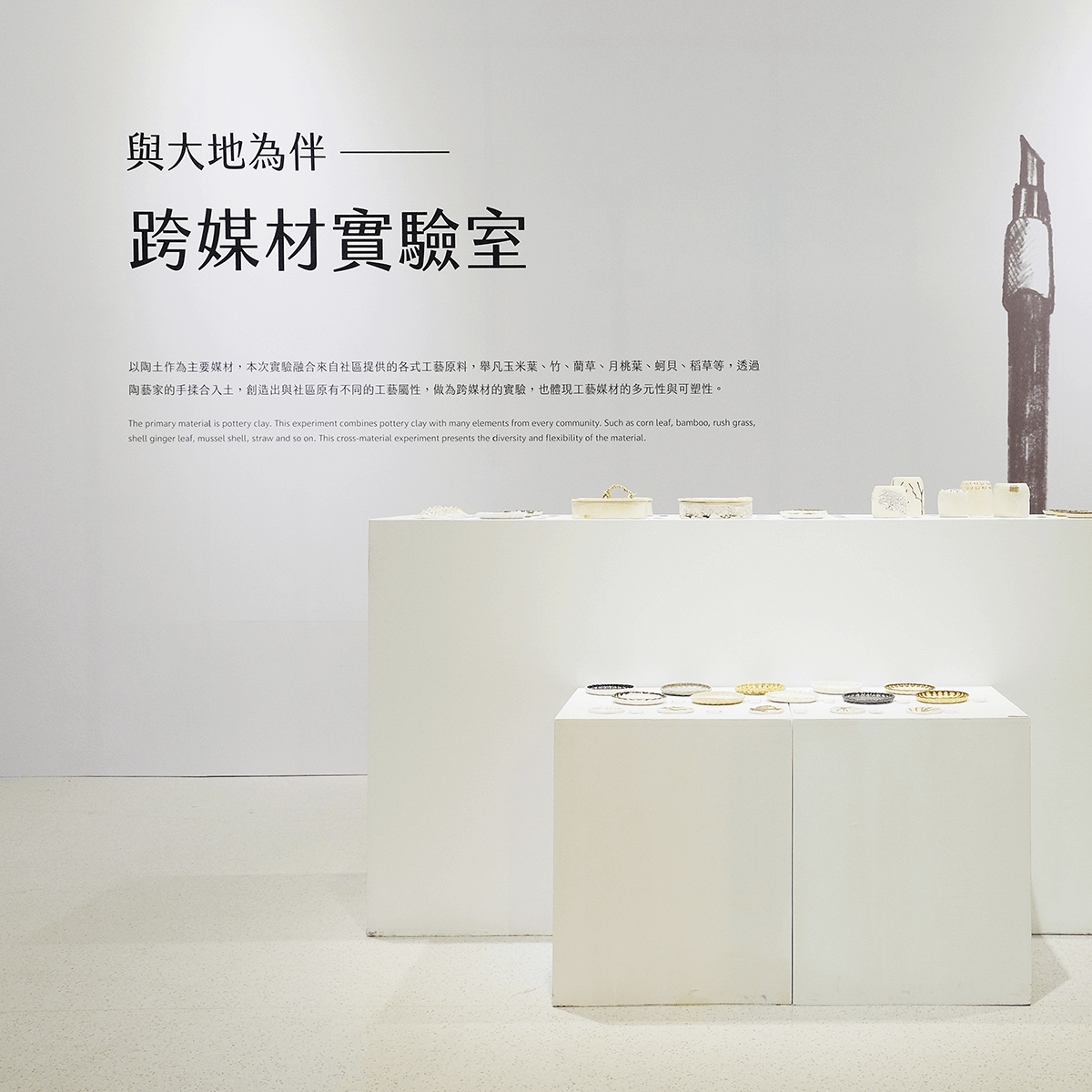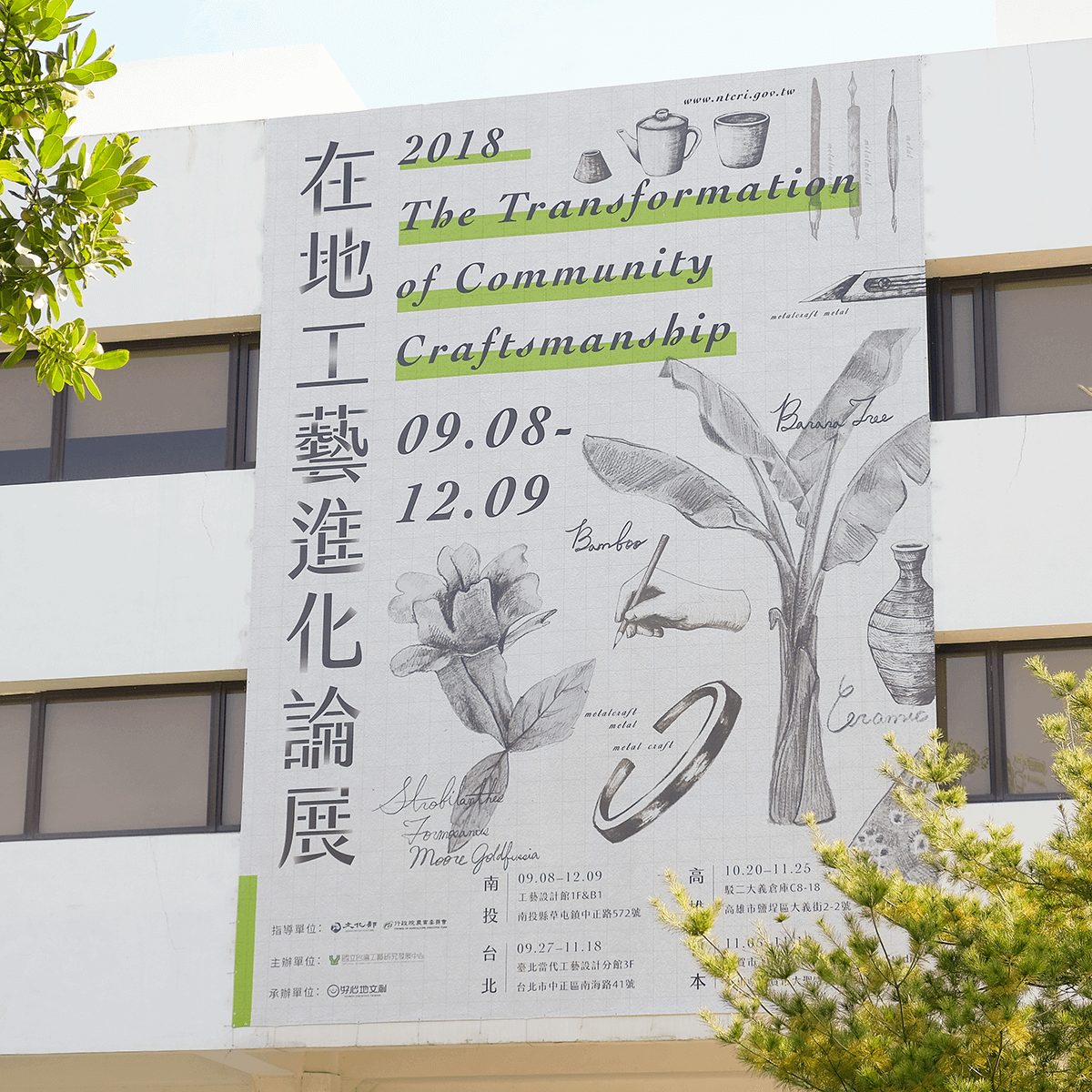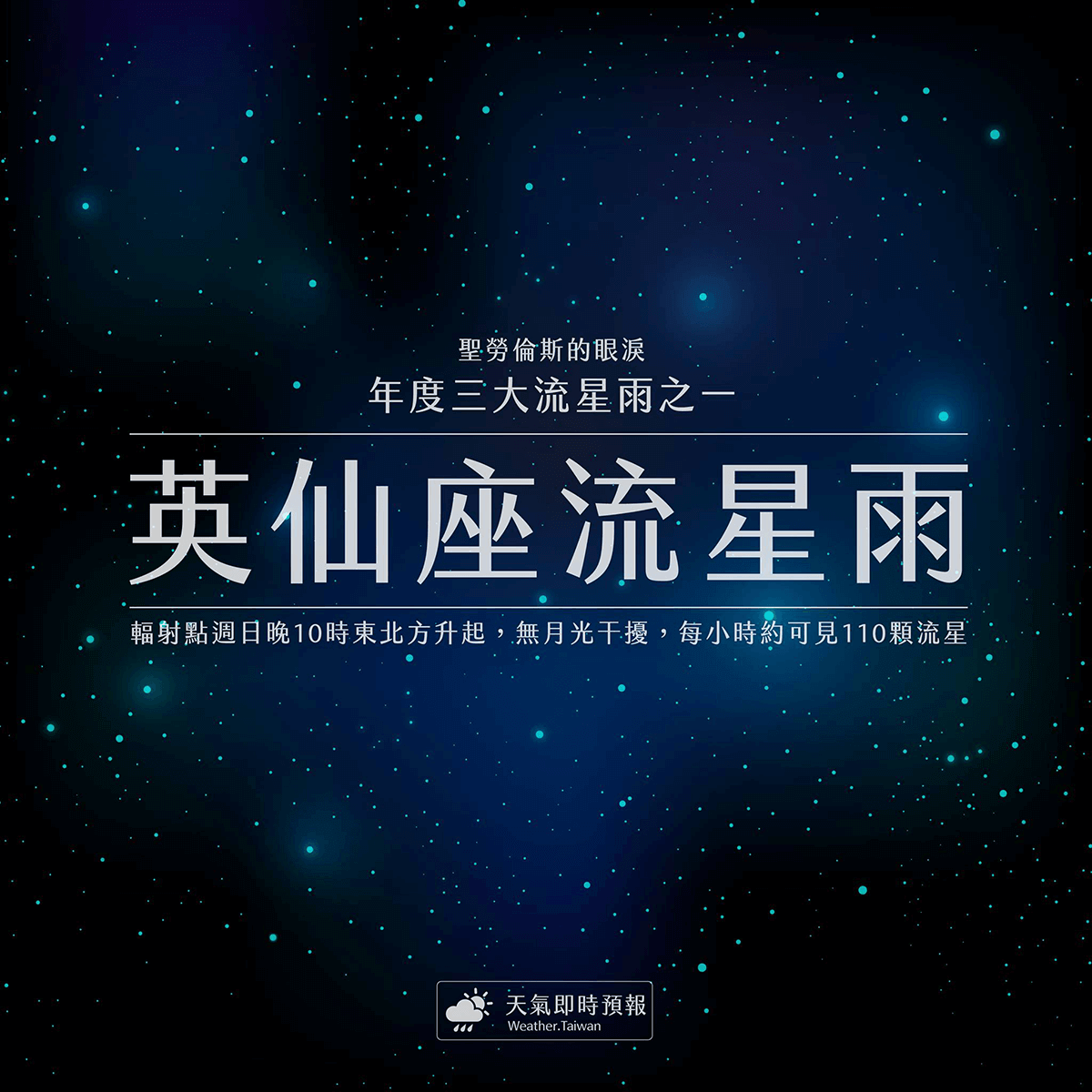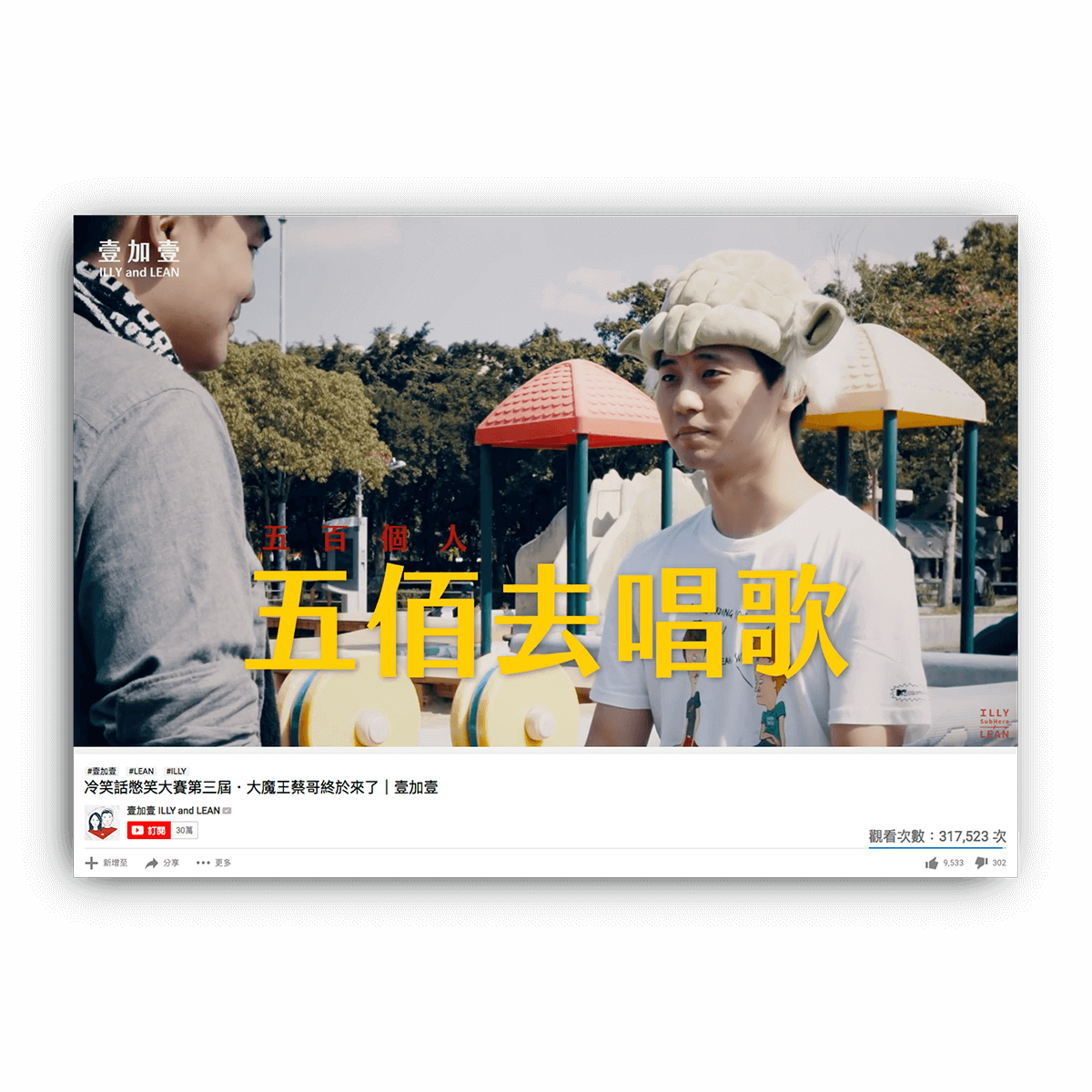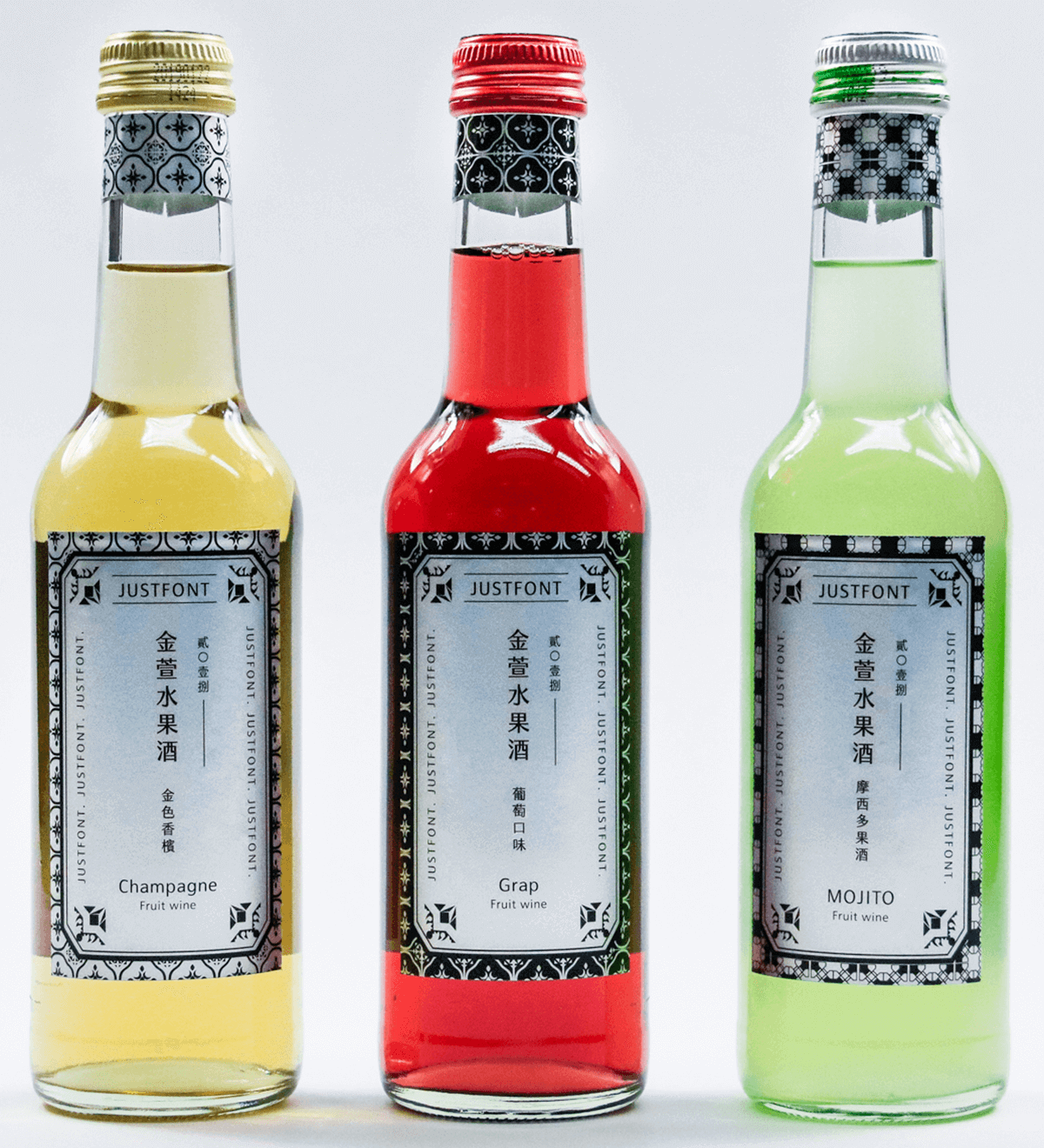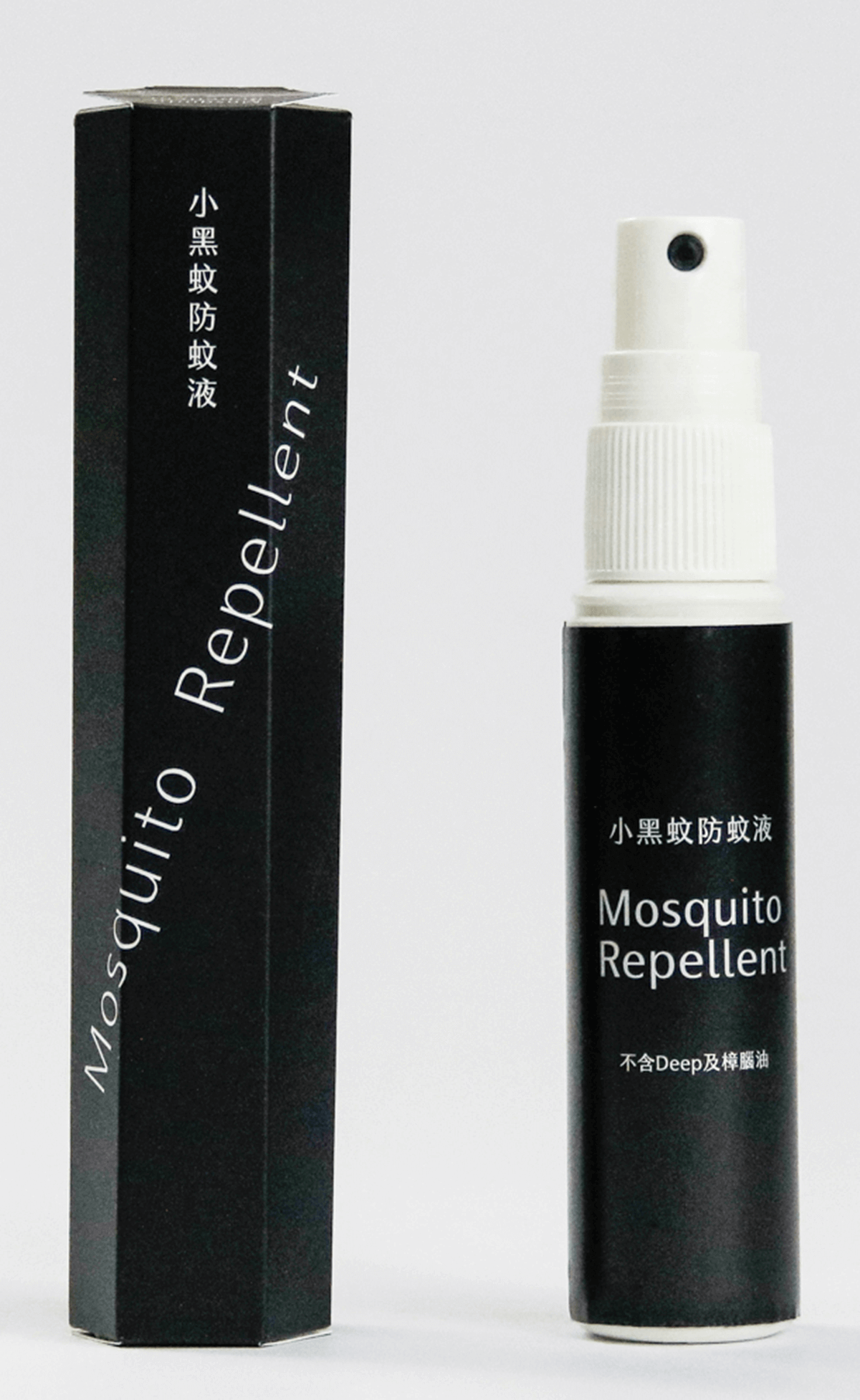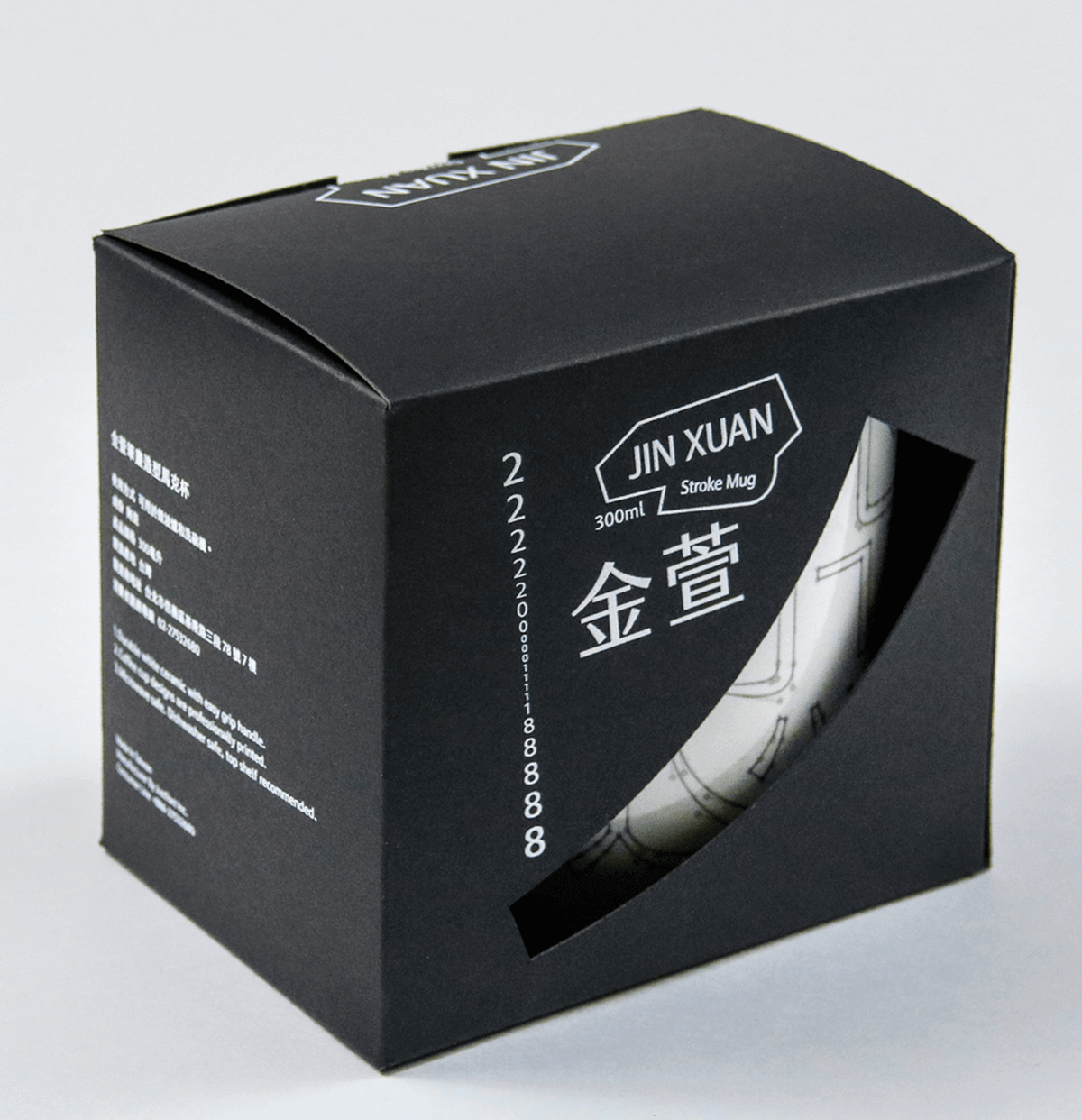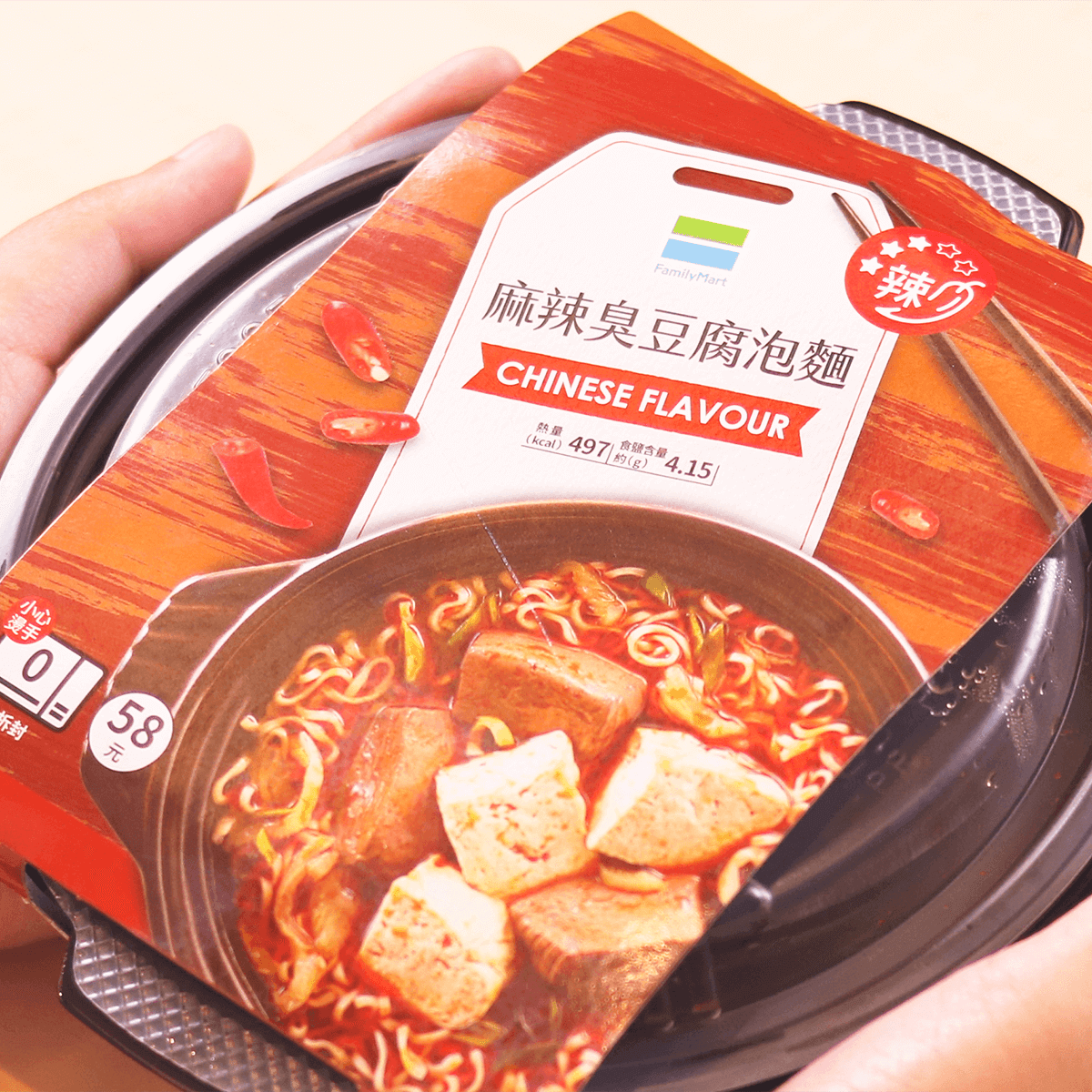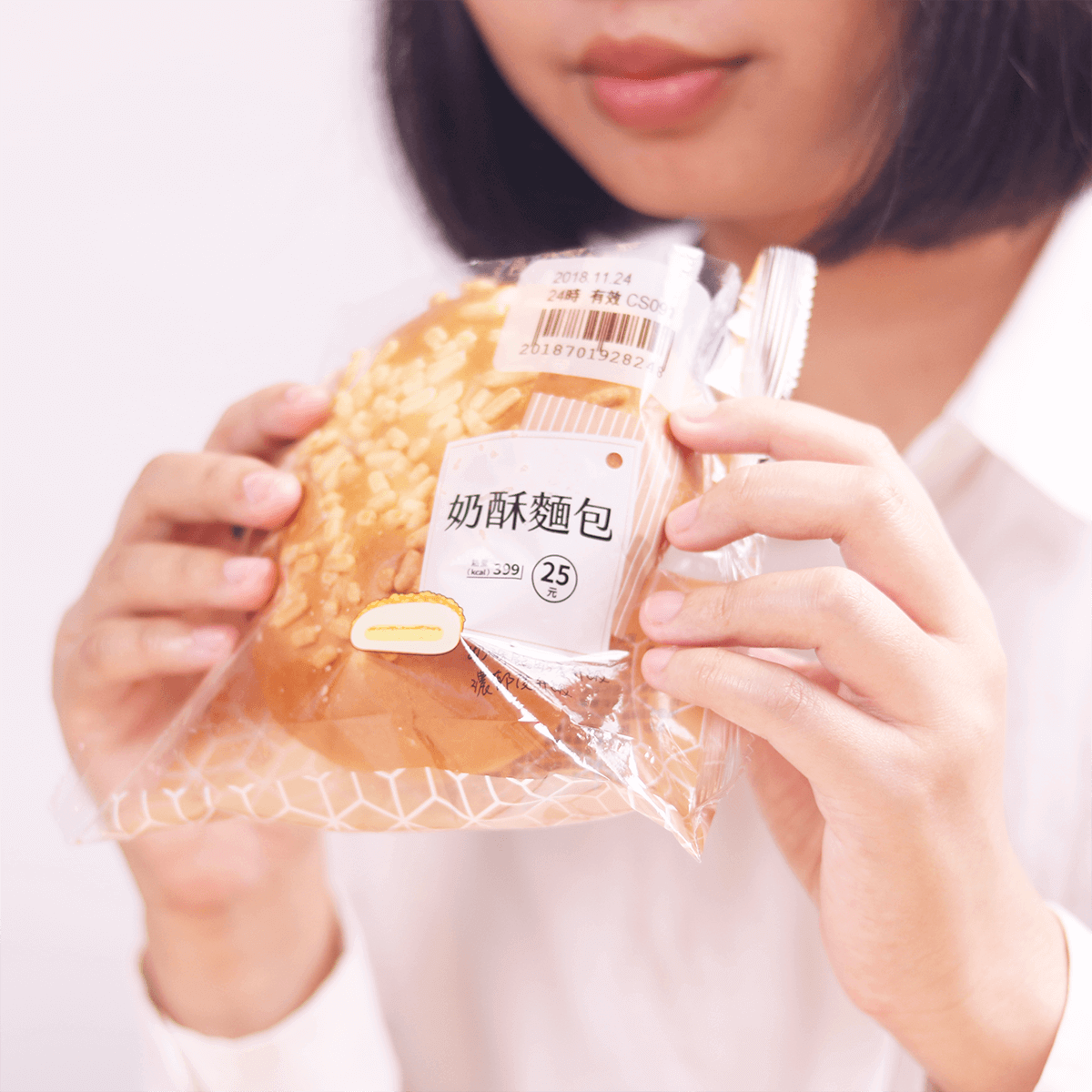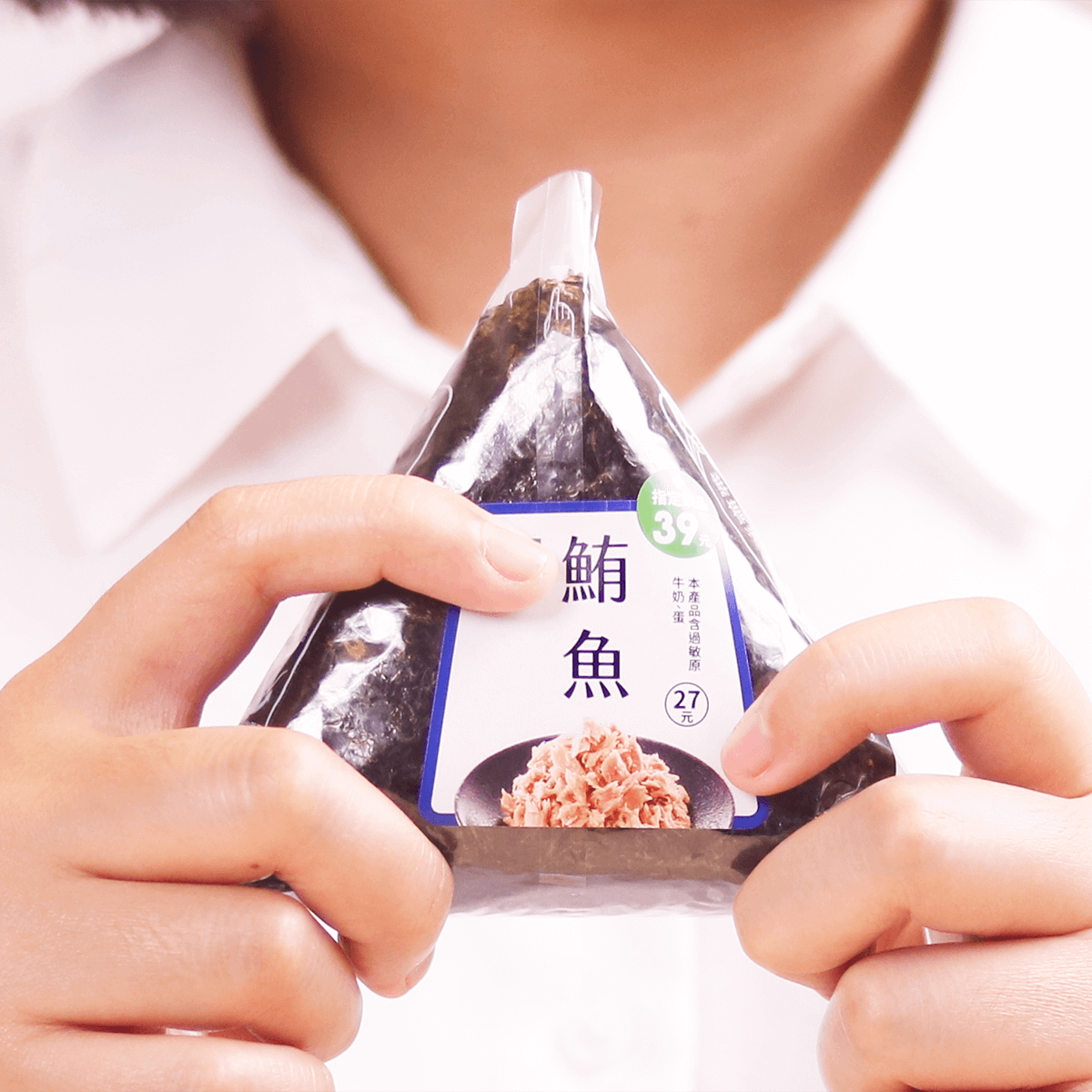
金萱
自 2016 年首先發佈「金萱半糖」後,我們觀察到文字的地貌正一點一點改變當中。金萱已經是台灣設計師、創作者最愛使用的字體之一。它已是書封、雜誌排版的常客。而不管是藝文展覽的海報、文化地標的招牌,或是網路上瘋傳的影片,甚至是超商點心食物的包裝,金萱字型更已經走進我們的生活中,成為編織文字風景的視覺纖維。你又發現多少有趣的應用了呢?
兩廳院瘋戲月
設計:洪添賢/藝文單位:兩廳院
Croter Illustration & Design Studio
金萱半糖
與大地為伴跨媒材實驗室
設計:好心地文創 / 展覽地點:國立臺灣工藝研究發展中心 設計館
金萱半糖
中山地下街誠品書店 R7
金萱半糖
在地工藝進化論展
設計:好心地文創 / 展覽地點:國立臺灣工藝研究發展中心 設計館
金萱半糖
書名:唯妖論 / 作者:台北地方異聞工作室 / 美術設計:蘇品銓
金萱半糖
字誌 - 字嗨探險隊
金萱半糖
影音創作者:好心地文創
影片名稱:2016 屏東老樹慶生 美崙社區
影音創作者:YouTuber壹加壹
影片名稱:冷笑話憋笑大賽第三屆・大魔王蔡哥終於來了
金萱七分糖
貼文標題: 英仙座流星雨
提供:天氣即時預報
金萱半糖
影音創作者:報導者
影片名稱:2018 報導者形象逐格動畫
金萱半糖、金萱三分糖
影音創作者:台灣吧
影片名稱:國家人權博物館 x 臺灣吧 TaiwanBar
金萱半糖
雙起司火腿握沙拉
金萱半糖
麻辣臭豆腐泡麵
金萱半糖
奶酥麵包
金萱半糖
鮪魚
金萱半糖
鮮奶吐司
金萱半糖
品名:玉里清酒
金萱半糖
小黑蚊防蚊液
Mosquito Repellent
金萱三分糖
清爽吸油面紙
金萱三分糖
金萱水果酒
金色香檳、葡萄口味、摩西多果酒
金萱半糖
小黑蚊防蚊液
Mosquito Repellent
金萱三分糖
馬克杯包裝
金萱半糖